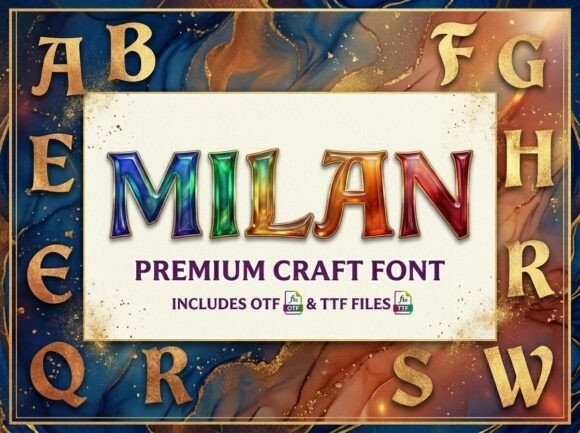
Milan
適切なデザイン要素を見つけるのは難しい場合がありますが、Milanは作品を即座に引き立てる優れたコレクションを提供します。
精密に作られたMilanは、クリーンなベクター、滑らかなタイポグラフィ、そして安心のための商用ライセンスを提供します。
POD(オンデマンド印刷)製品、結婚式の招待状、またはソーシャルメディアのグラフィックを作成している場合でも、Milanは理想的です。